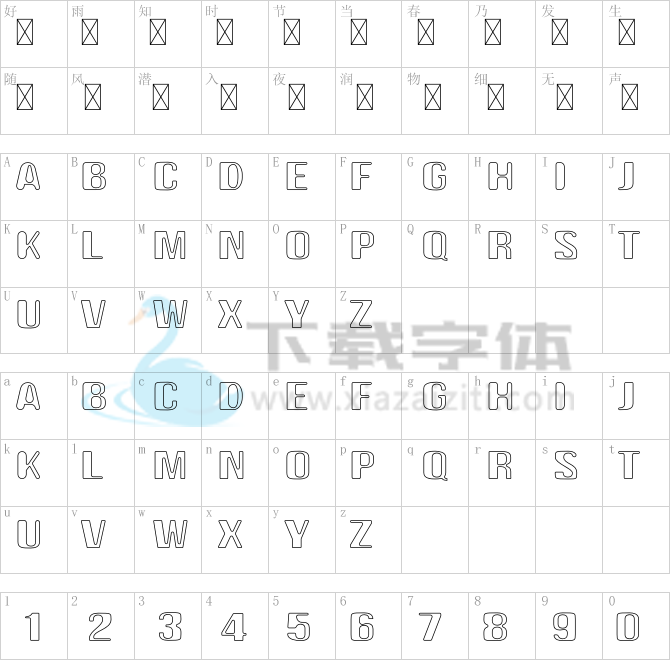
Alien Space Outline.otf字体下载,这款字体结构工整、笔画清晰,兼顾美观与易读性,适用于标题、正文、海报、包装、LOGO 等多种场景。字形优雅稳定,风格百搭耐看,适配日常排版与创意设计,让文字呈现更舒适、更具质感。Alien Space Outline.otf字体下载一笔一画,皆是细节,以均衡的比例、流畅的线条打造舒适视觉体验,字形端正大气,风格简约现代。无论是商业设计、品牌宣传还是日常排版,都能轻松驾驭,让文字更有格调与力量。Alien Space Outline.otf字体下载字体下载。